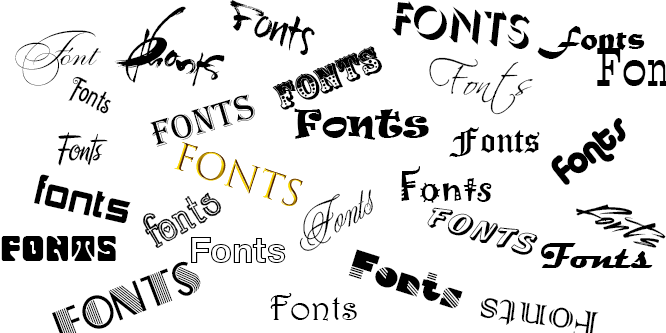
Làm thế nào để lựa chọn được Font chữ cho website phù hợp nhất? Câu trả lời của bạn là nội dung trong bài viết dưới đây.
Font chữ trên web chuẩn, dễ đọc
Font chữ chuẩn được dùng trên web có size từ 12 – 14.
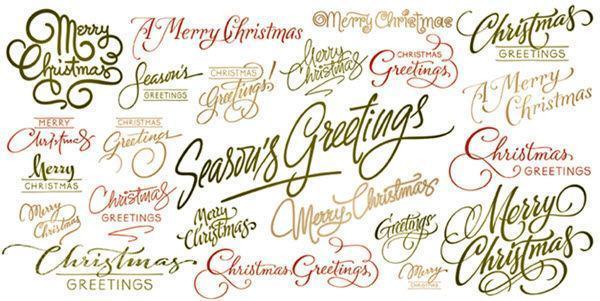
Màu sử dụng cho Font chữ bạn cũng nên lưu ý cần phù hợp với nền, không quá gần với màu nền nhưng không nên quá tương phản với màu nền vì nó sẽ gây khó khăn cho người đọc.
Lựa chọn Font chữ phù hợp
Font chữ trên website không nên quá rắc rối vì nó sẽ khiến người đọc mất tập trung. Font chữ bạn nên lựa chọn phù hợp với nội dung của website, mang phong cách dành riêng cho nhóm đối tượng xác định.
Ví dụ: Với website dành cho trẻ em, hoặc cho mẹ và bé bạn cần lựa chọn Font chữ mang phong cách ngộ nghĩnh, màu sắc. Ngược lại website cho người lớn cần có Font chữ đơn giản dễ nhìn, rõ ràng.
Nên dùng một loại Font cho website
Một website tốt nhất là không nên quá 3 Font chữ khác nhau để tránh tạo cho người đọc sự rối mắt, thiếu thẩm mỹ.
Bạn nên sử dụng cùng một loại Font chữ cho toàn bộ trang web của mình, kể cả kích thước của Font ở từng phần, các thẻ giống nhau cũng nên giống nhau.
Chỉ nên dùng những Font tiêu chuẩn
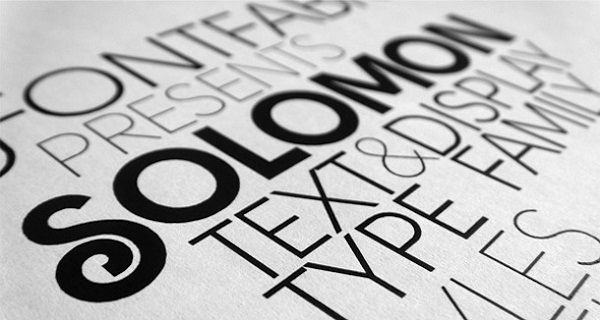
Khi sử dụng tiếng việt cho website bạn nên dùng các Font Unicode chuẩn như Times News Roman, Verdana, Tahoma, hay Arial…
Sử dụng công cụ kiểu chữ
Với nhiều Font chữ cho website bạn thích nhưng lại không đạt chuyển vì nó sẽ thay đổi trên các trình duyệt khác nhau. Vì vậy hãy sử dụng các dịch vụ trên các website sau để có được cho web mình được một font chữ chuẩn:
– Google Web Fonts: Cho phép cấp phát Font chữ miễn phí phù hợp cho thiết kế trang web với mã nguồn mở.
– What The Font: Cho phép bạn nhập URL của hình ảnh hoặc tải lên một tập tin hình ảnh nào đó để tìm tên của Font chữ trong câu hỏi.
– Flipping Typical: Cho phép bạn nhập văn bản và so sánh với các mẫu trong hàng trăm Font chữ phổ biến khác.
– Font Squirrel và Lost Type Co-Op: Đây là một bộ sưu tập chất lượng cao của Font chữ miễn phí mà có lẽ bạn nên thử qua.
– CSS Typeset: Tương tác style với kiểu chữ CSS sẽ tạo ra kết quả CSS cho việc sử dụng của bạn.
Như vậy có thể nói việc lựa chọn Font chữ cho website chưa bao giờ là đơn giản. Để website của bạn có 1 giao diện thật đẹp và thật chuyên nghiệp, hãy ghi chú ngay 5 lưu này vào sổ tay của bạn nhé.